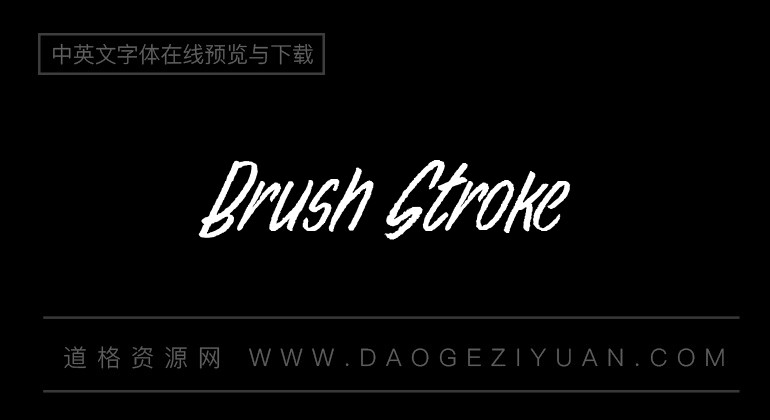
Brush Stroke 字体是一种手写字体,它具有优雅、自然、自由的特点,适合用于插画、海报、海报、文字等设计项目中。它的特点是每个字母都有一种粗犷的笔触,每个字母都有一种独特的质感,能够表达出自然、自由的气息。它的字体结构完整而稳定,能够满足大多数设计项目的需求,并且可以根据设计师的要求进行定制。内容介绍
Brush Stroke是一款非常不错的手写艺术字体,具有很好的视觉感,适合于文化类的宣传设计、商业类品牌的广告和产品包装设计以及个性化文字排版等较多场景。